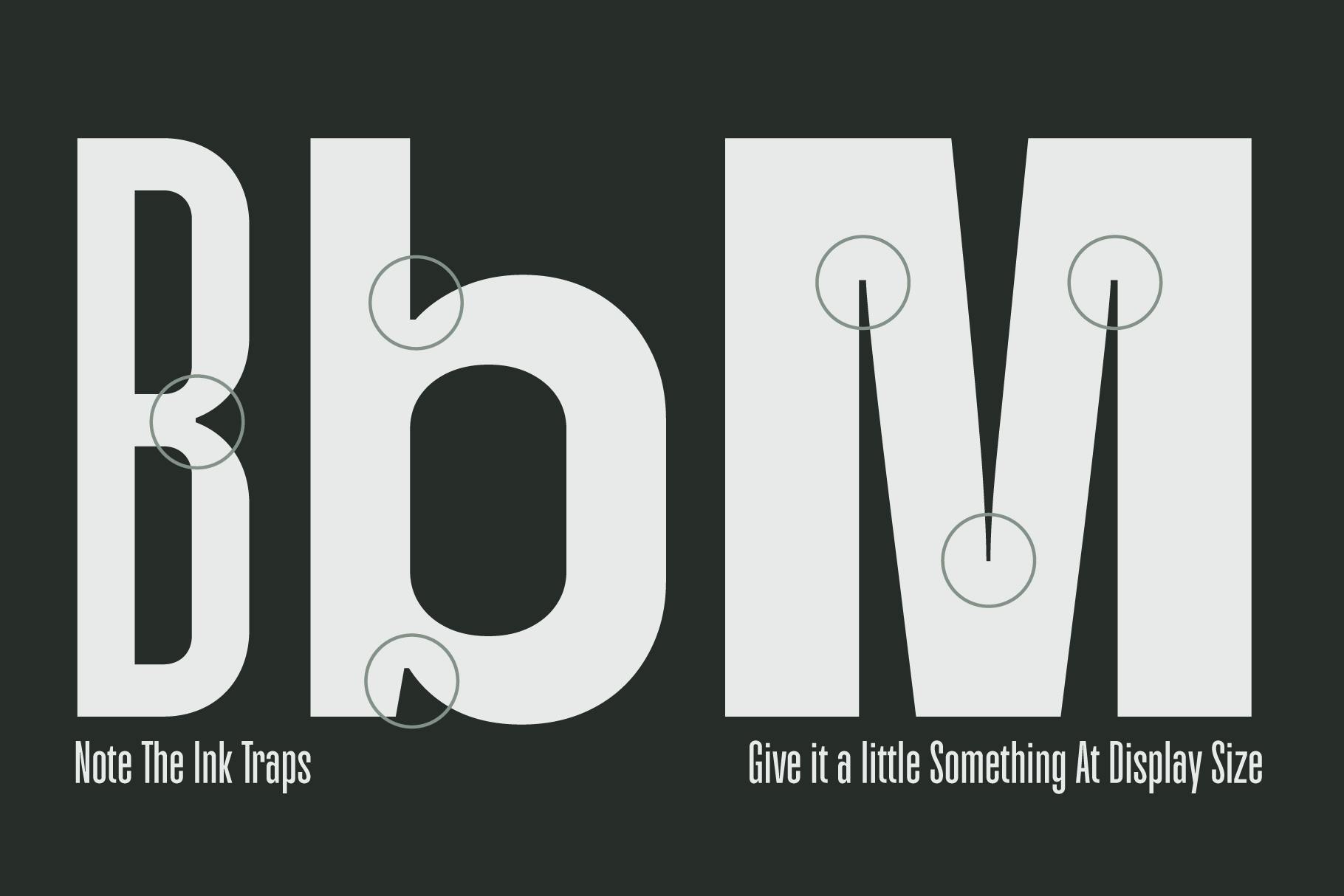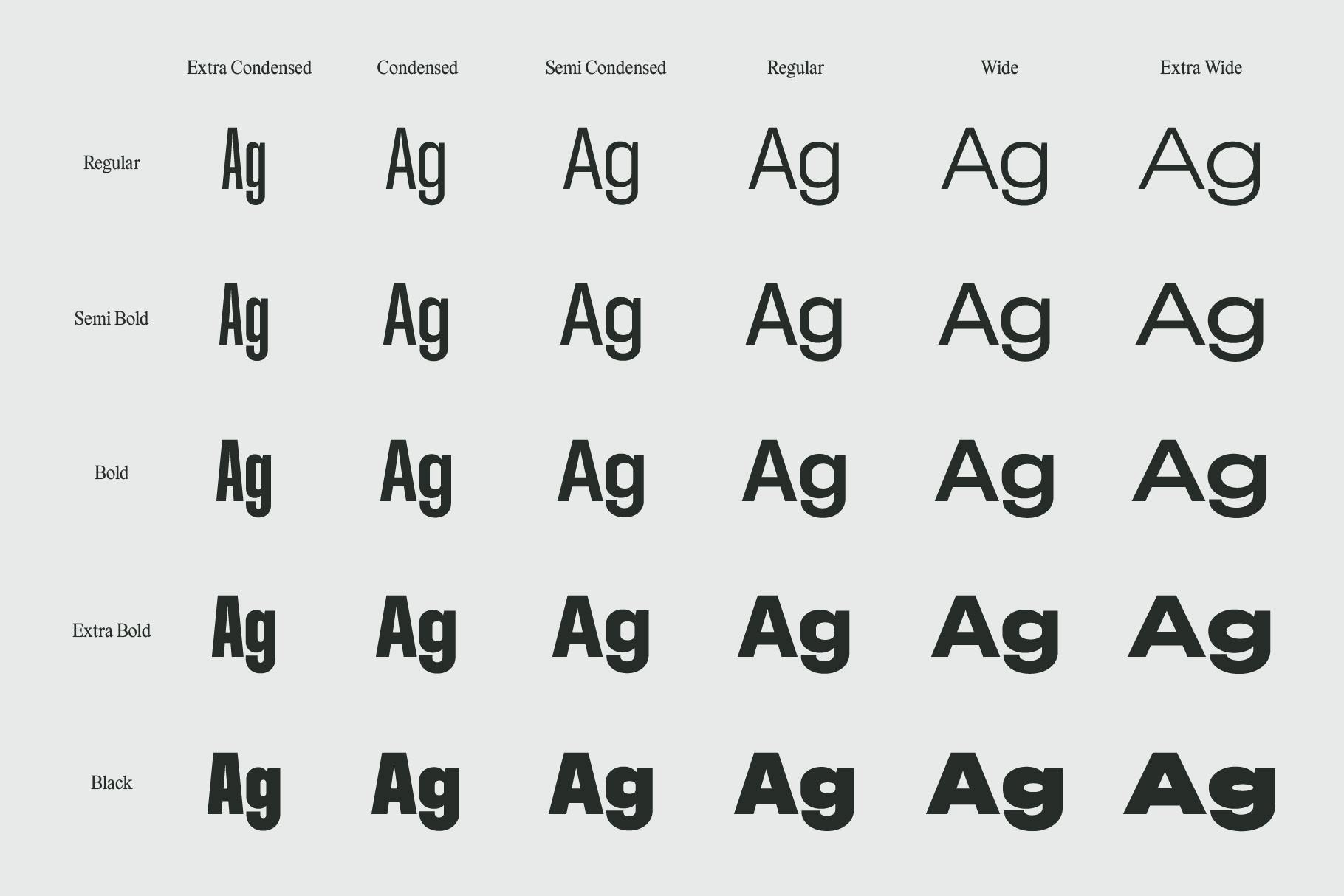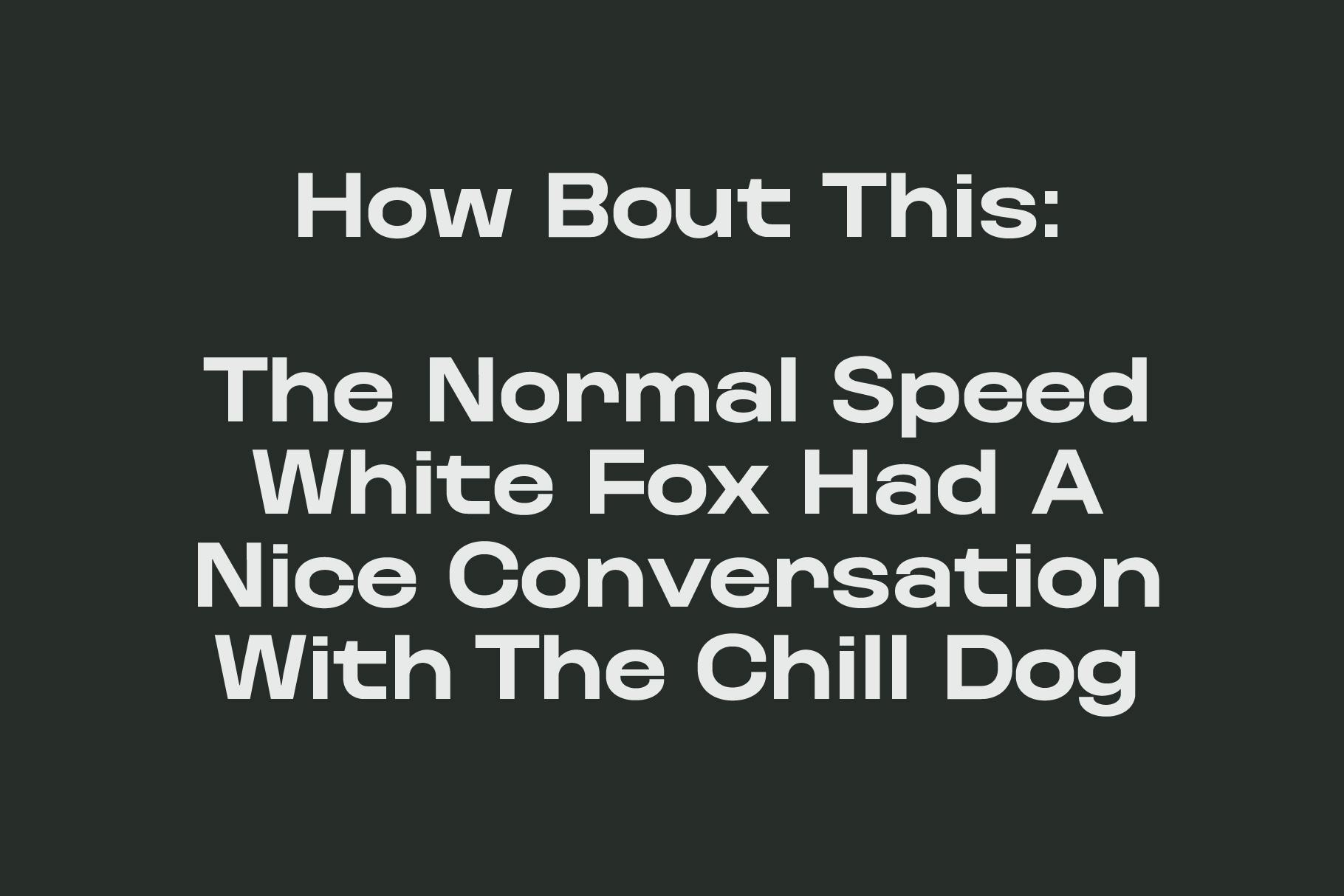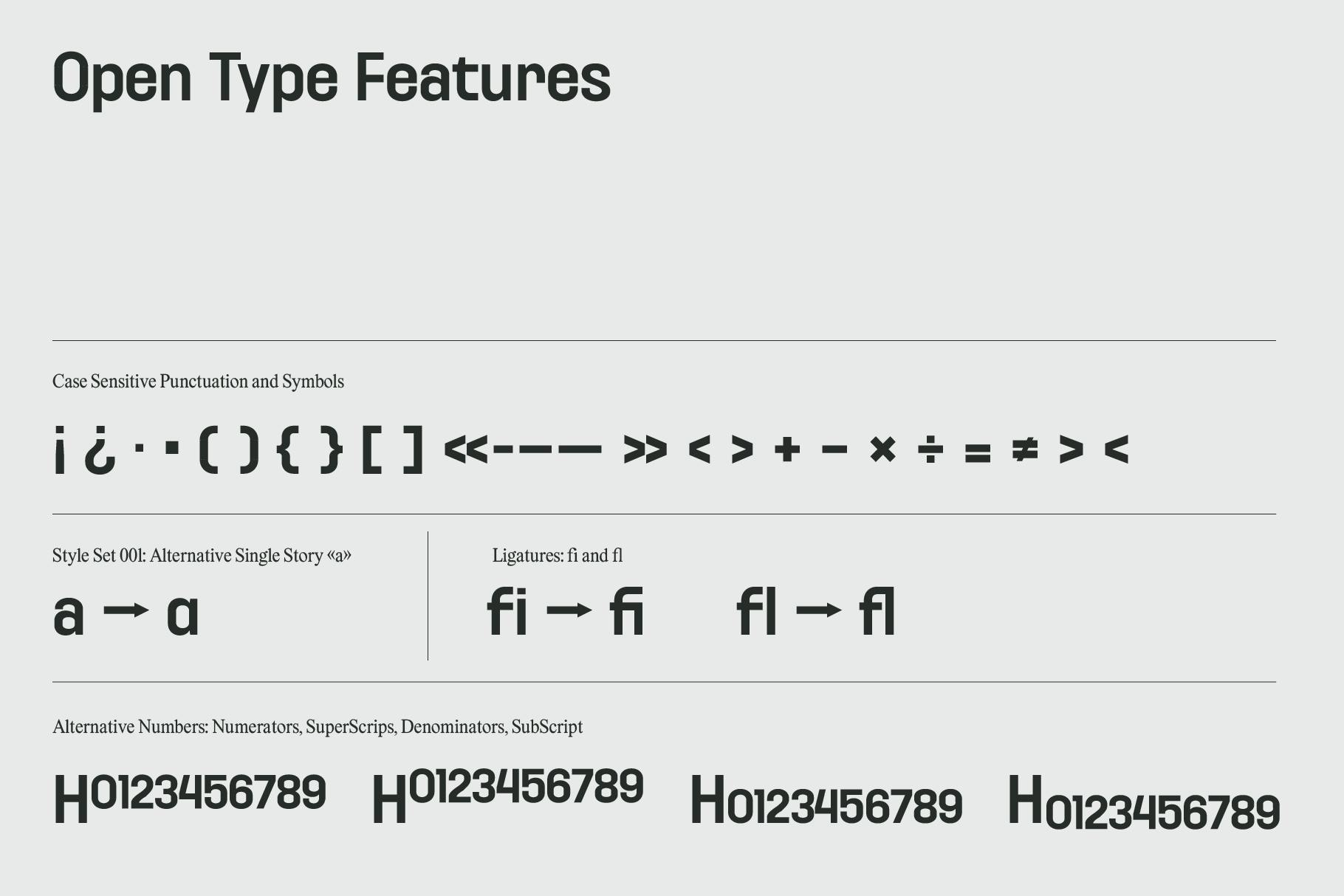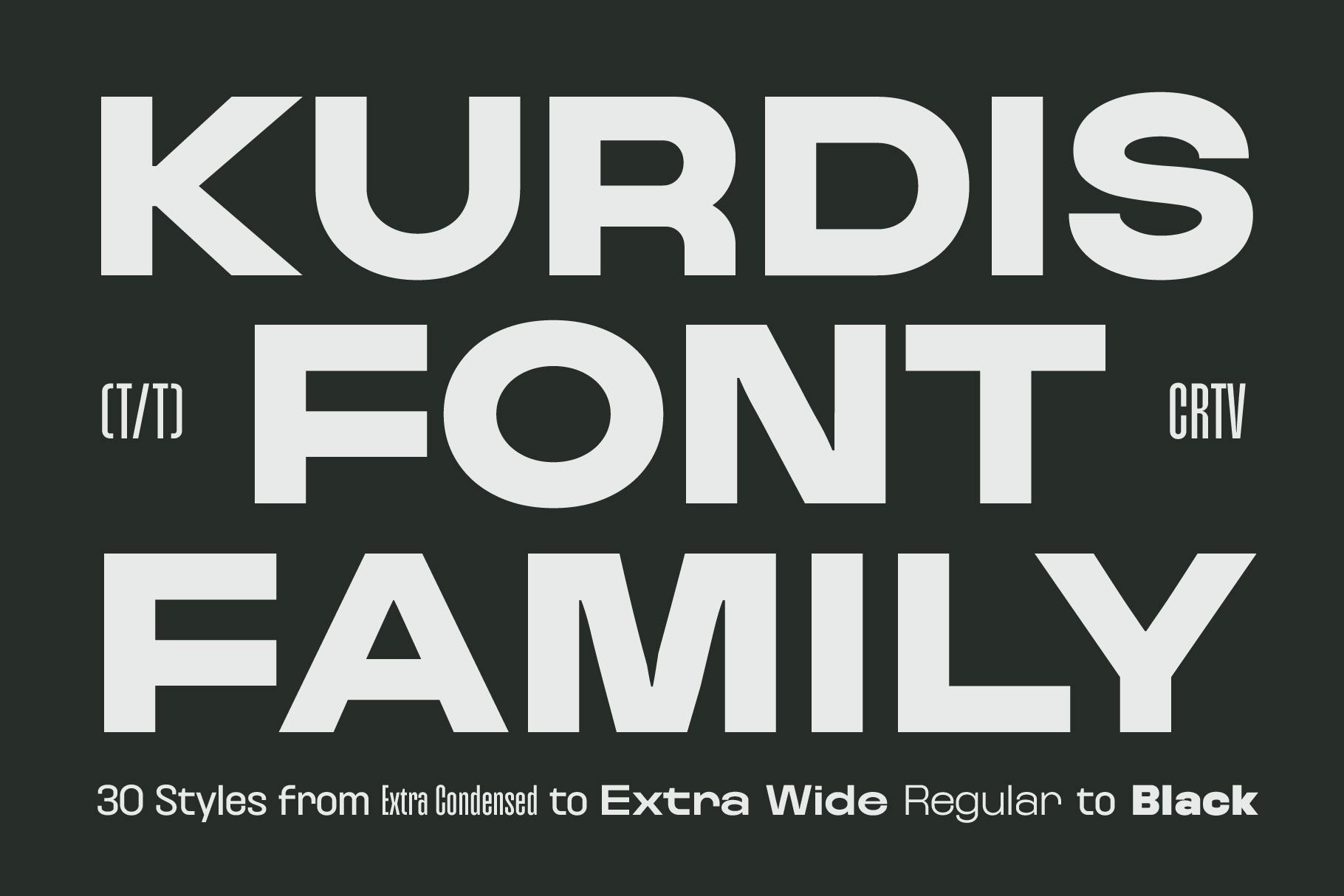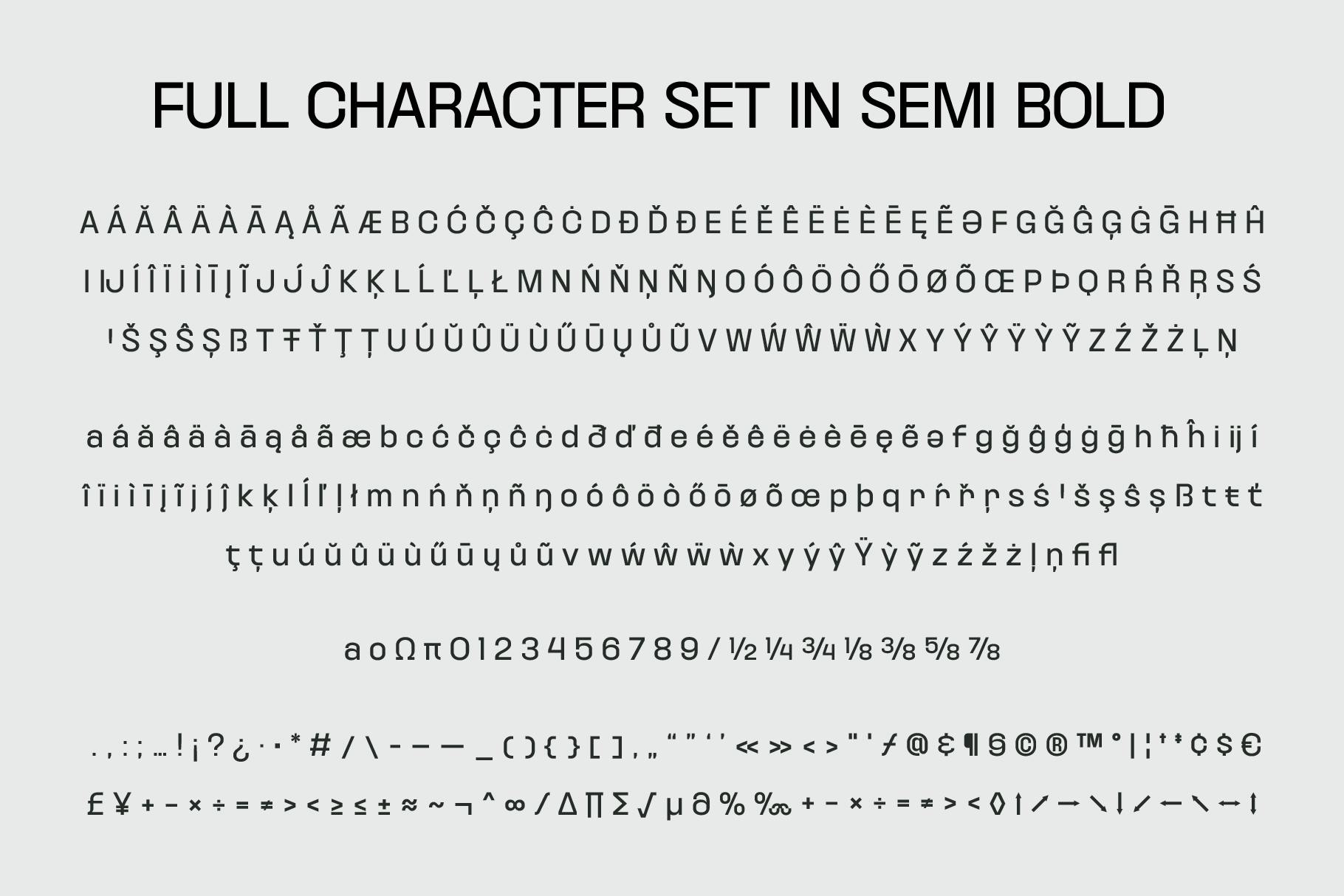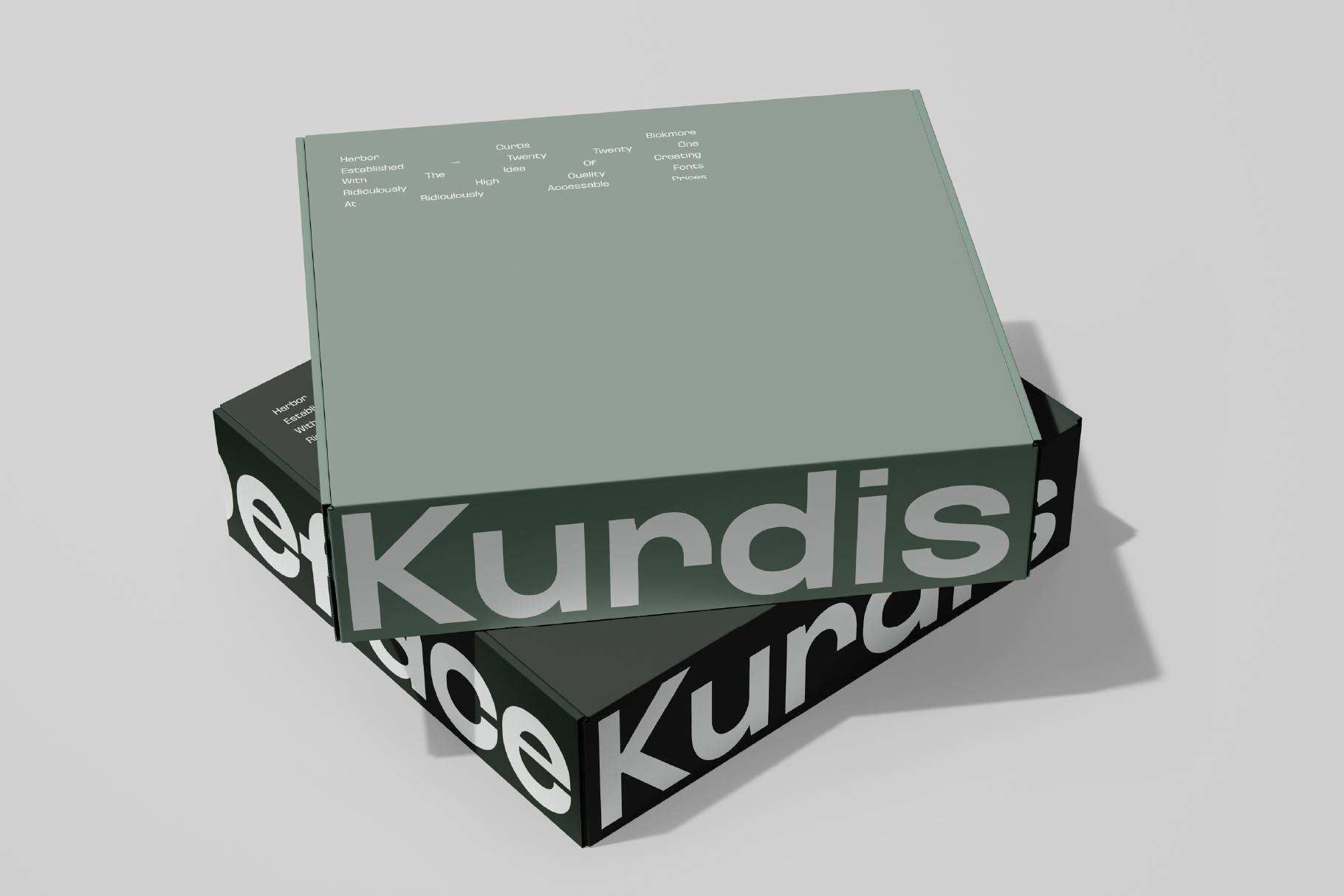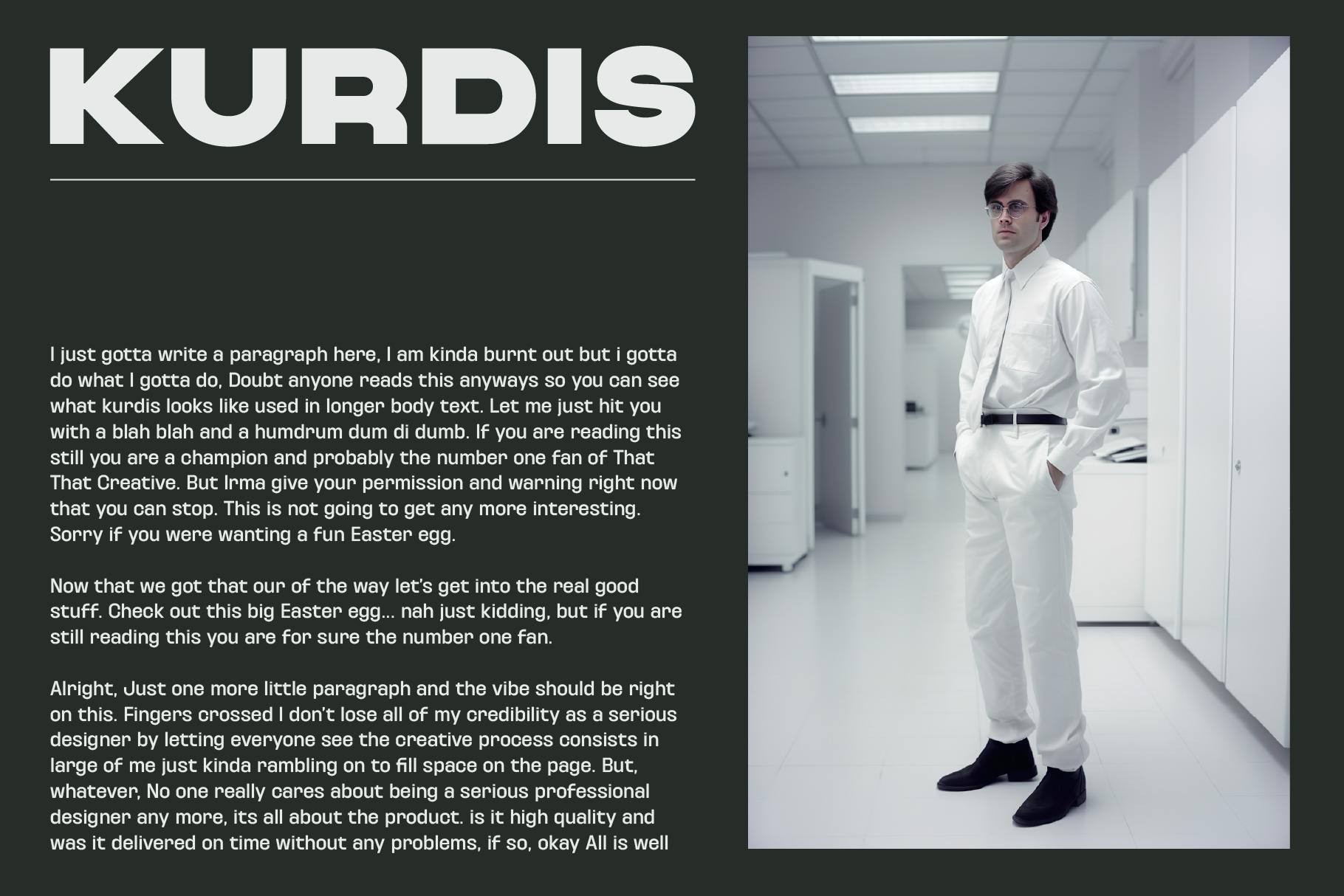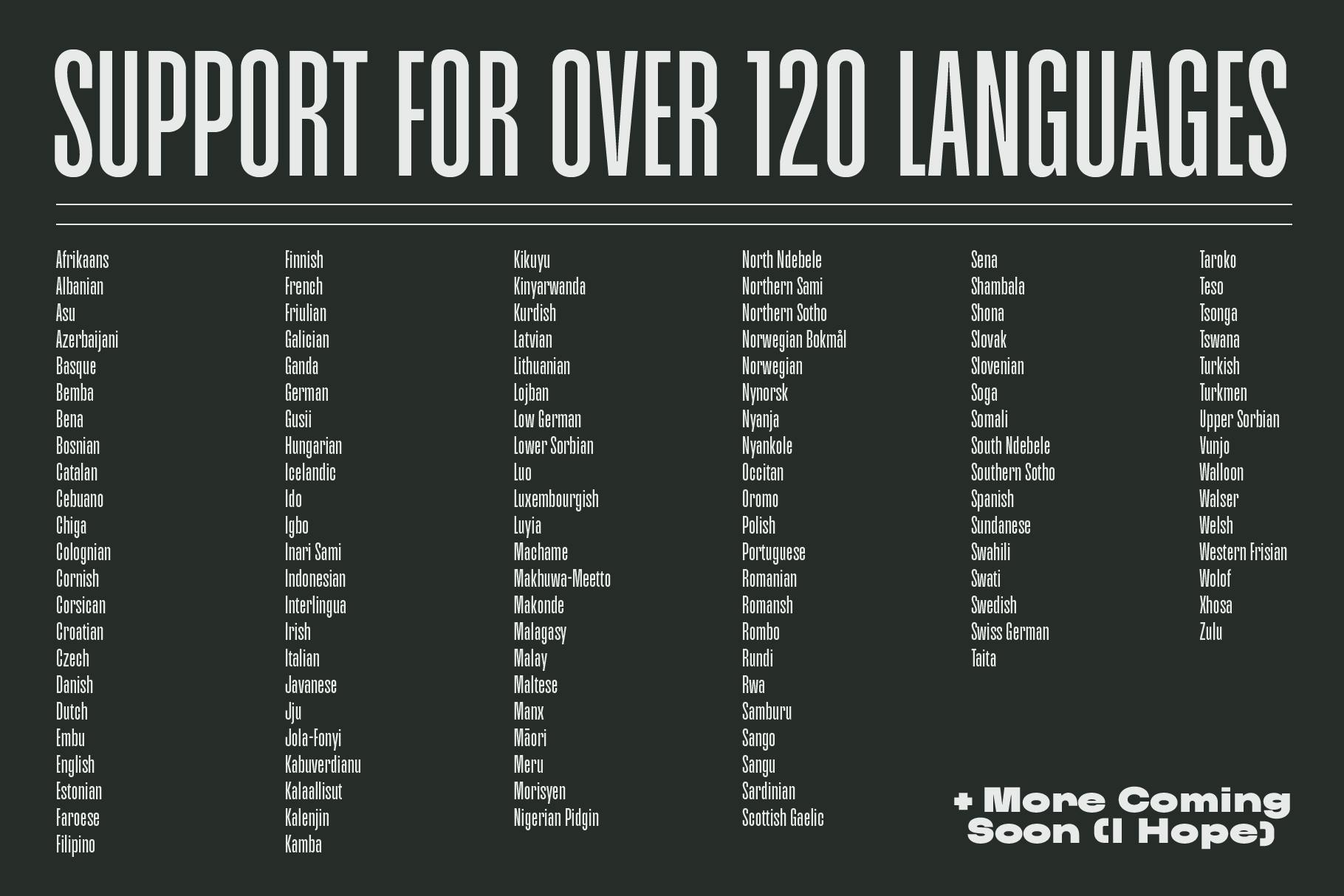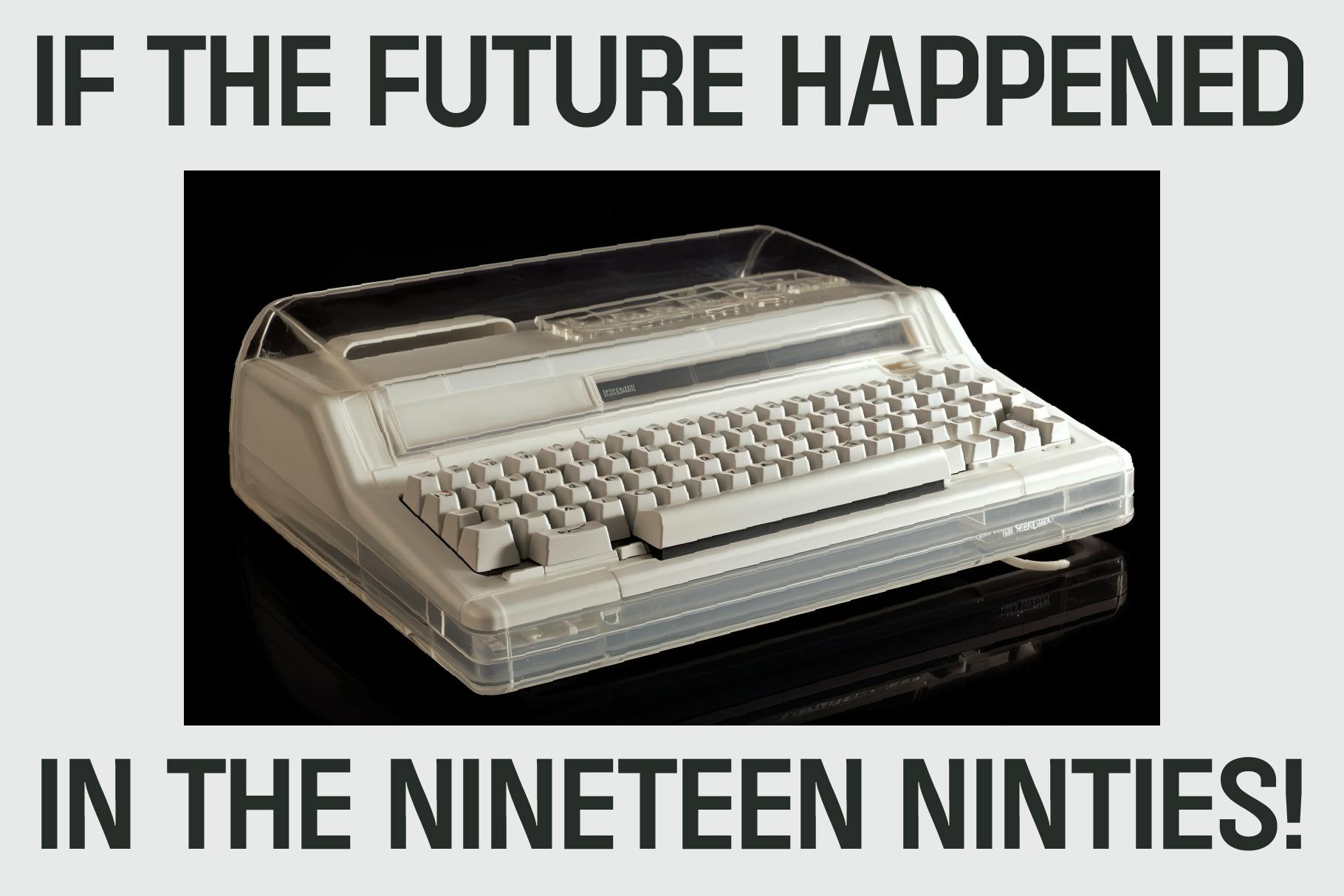
خانواده فونت Kurdis یک فونت مدرن بدون سریف است که شامل شش عرض و پنج وزن میباشد و به طور کلی ۳۰ استایل را ارائه میدهد. با توجه به گزینههای متغیر، این فونت قابلیتهای ترکیبی بیشتری نیز دارد. این نوع فونت برای عناوین بسیار مناسب است. در عرض فشردهاش، به شکلی پیچیده و حرفهای به نظر میرسد و تلههای جوهری خوبی دارد که باعث میشود در اندازههای بزرگ به خوبی جلوه کند. عرض معمولی آن برای متنهای طولانی در وبسایتها یا پوسترها مناسب است و استایلهای عریض ظاهری برجسته به فونتهای بدون سریف عادی میبخشند.